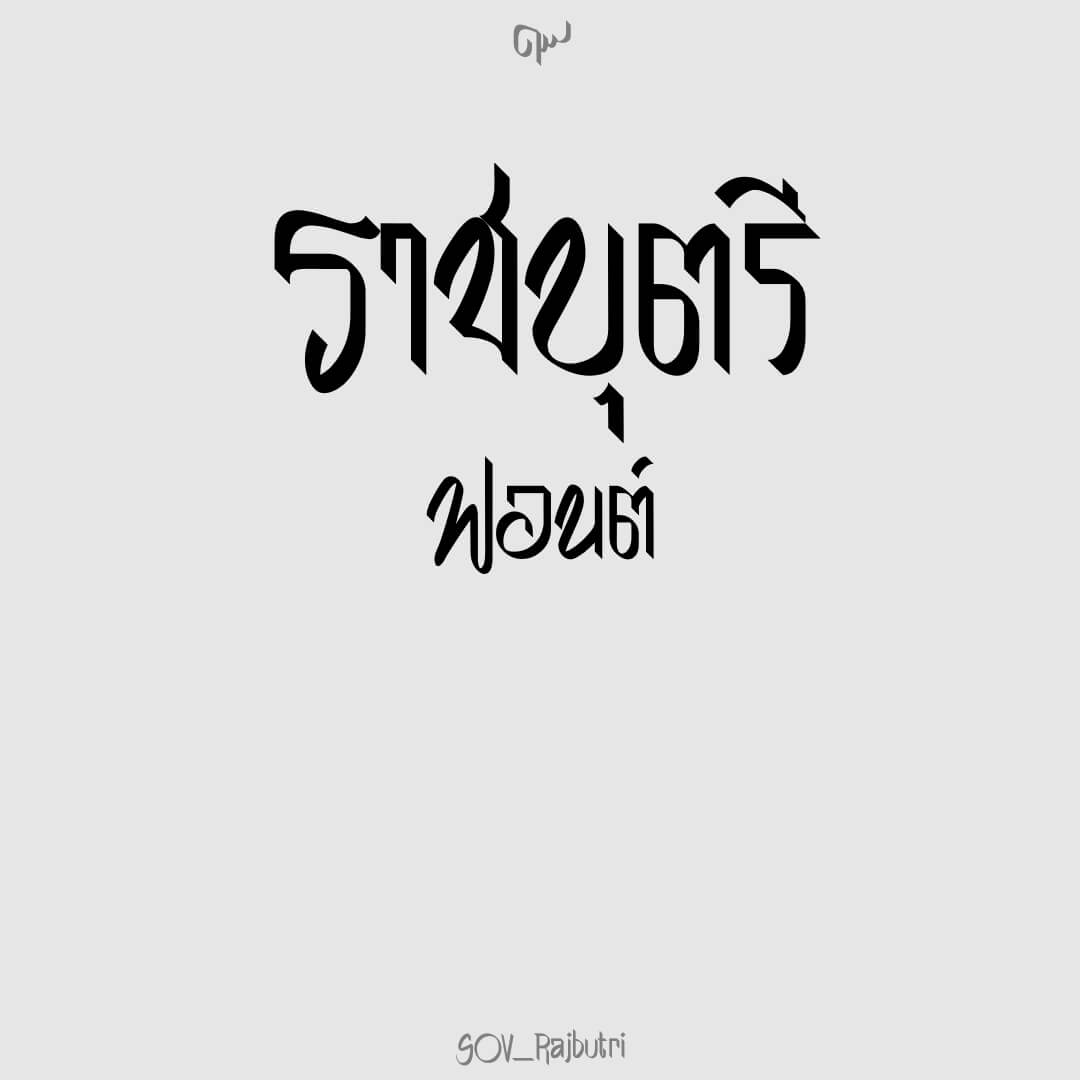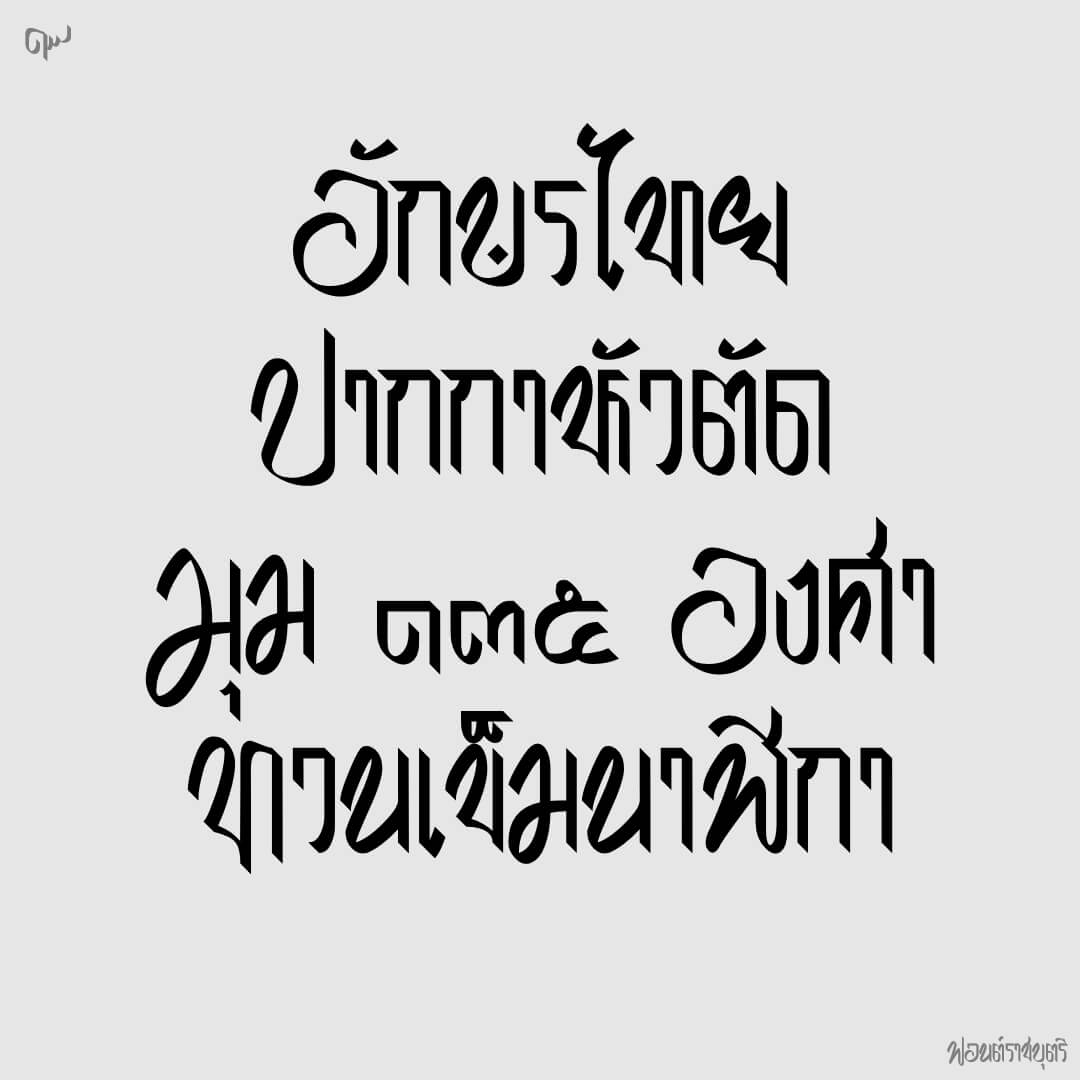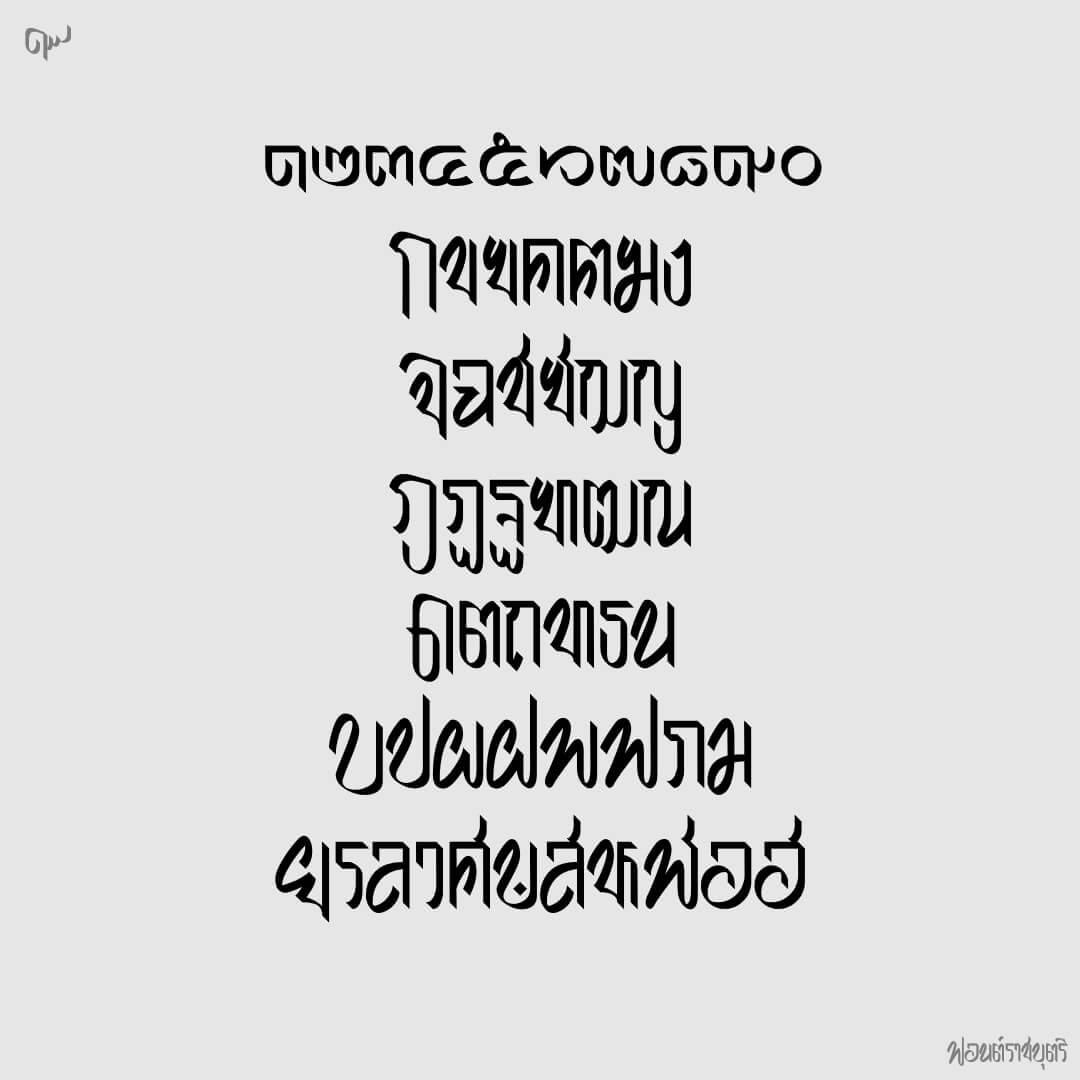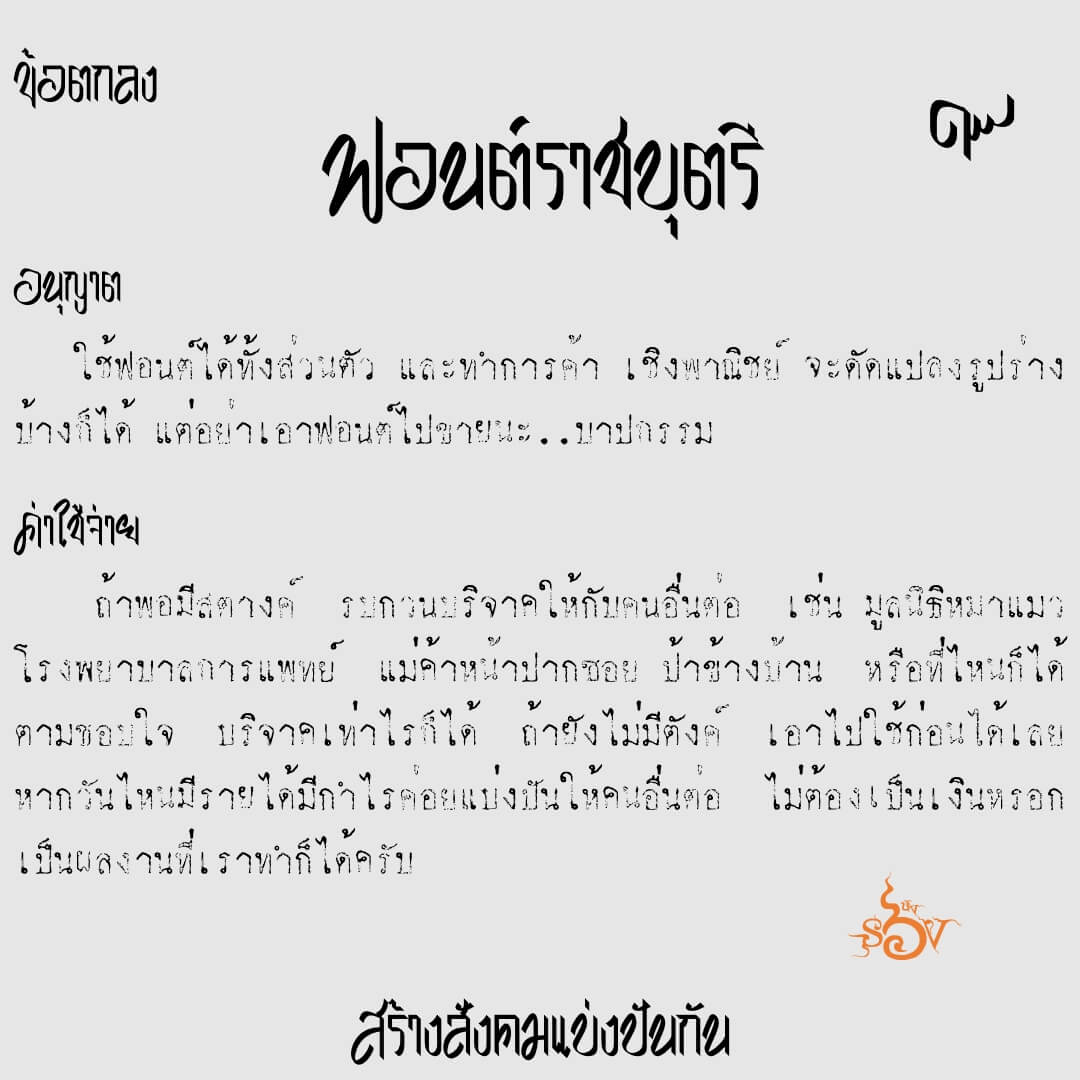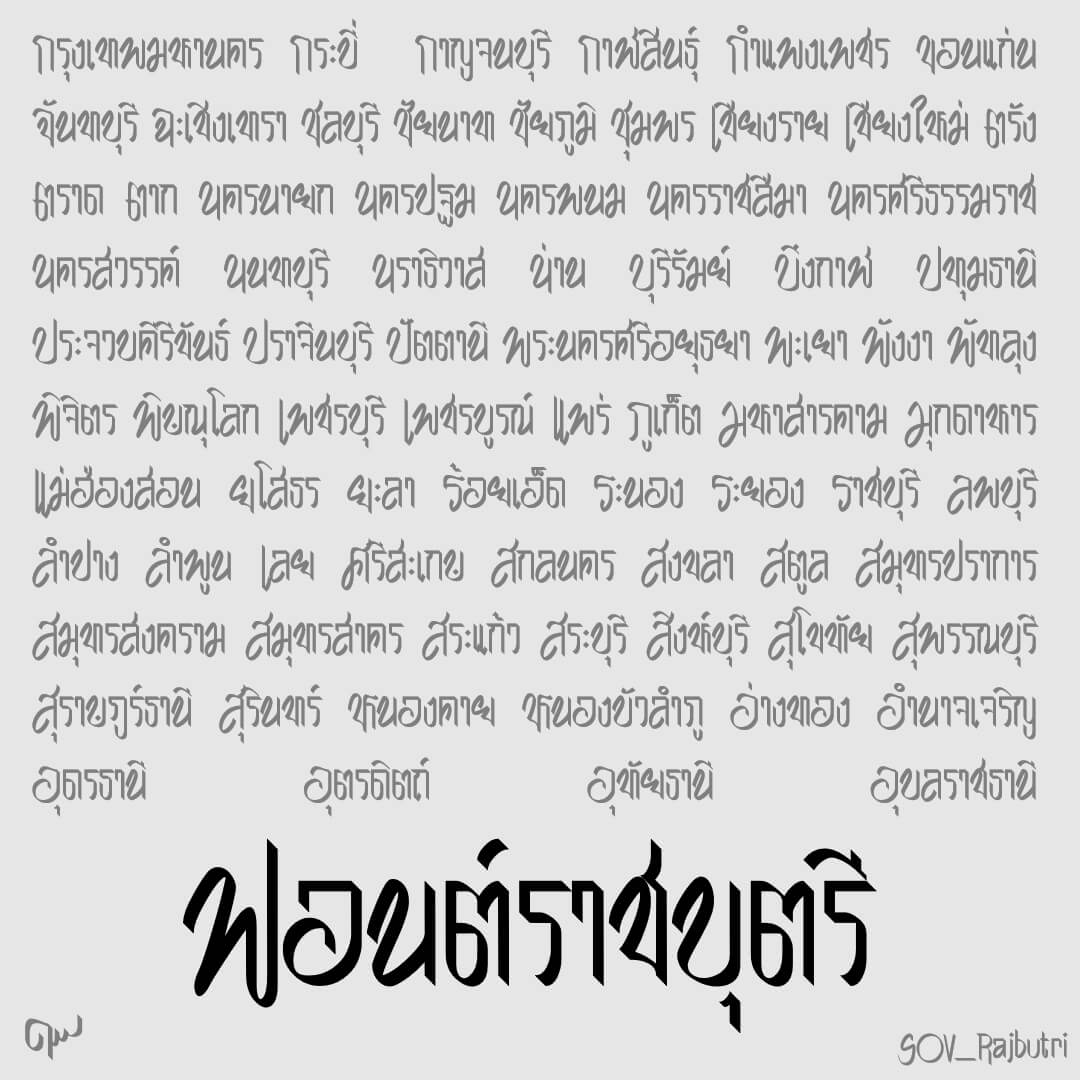
ฟอนต์ราชบุตรี – ฟอนต์ปากกาหัวตัด มุม 135 องศา ต่อยอดมาจาก ฟอนต์ราชบุตร อักษรตัวแรกตัวใหญ่กว่าตัวอื่น
เบื้องหลังการออกแบบ : ฟอนต์ ราชบุตรี
ราชบุตรี (SOV_Rajbutri)